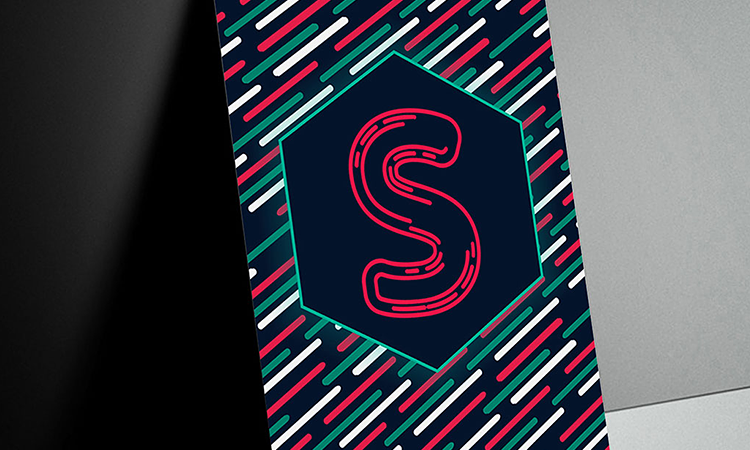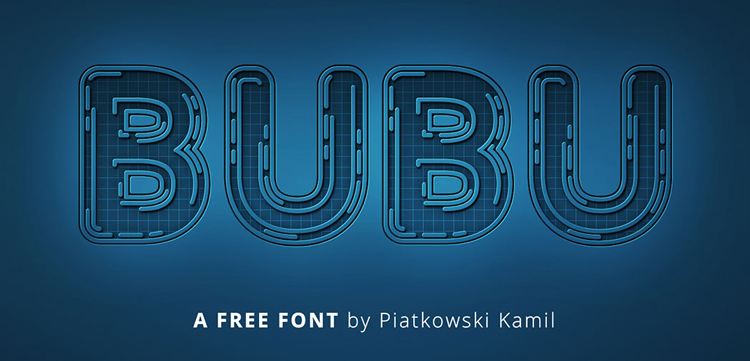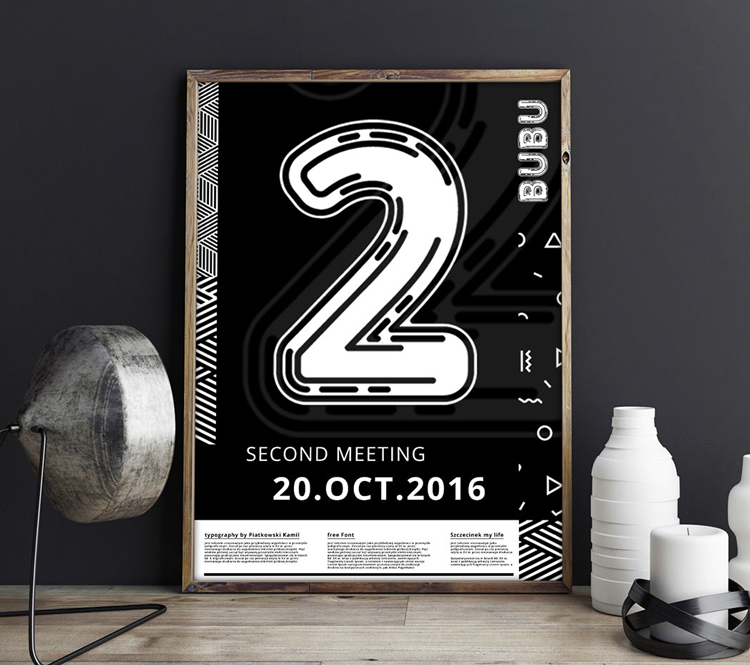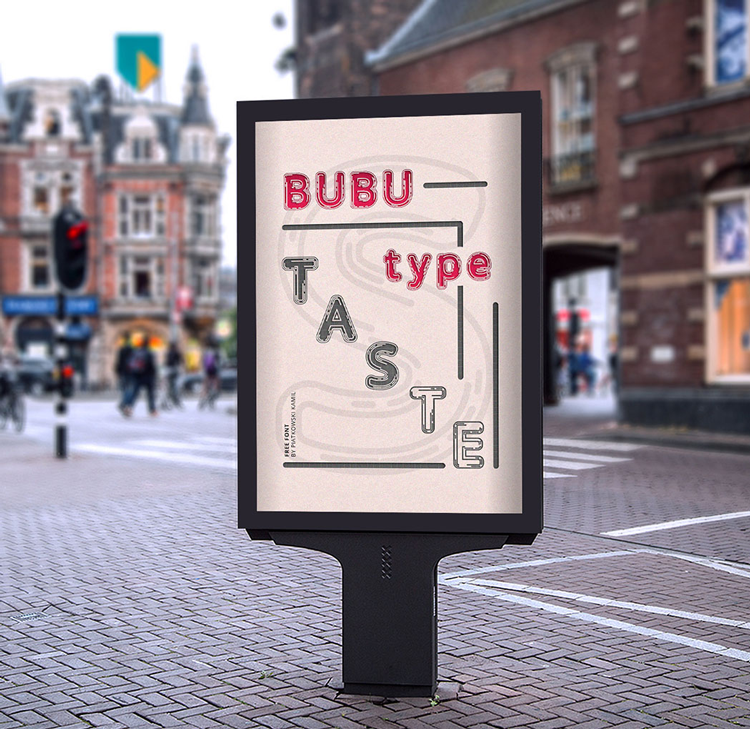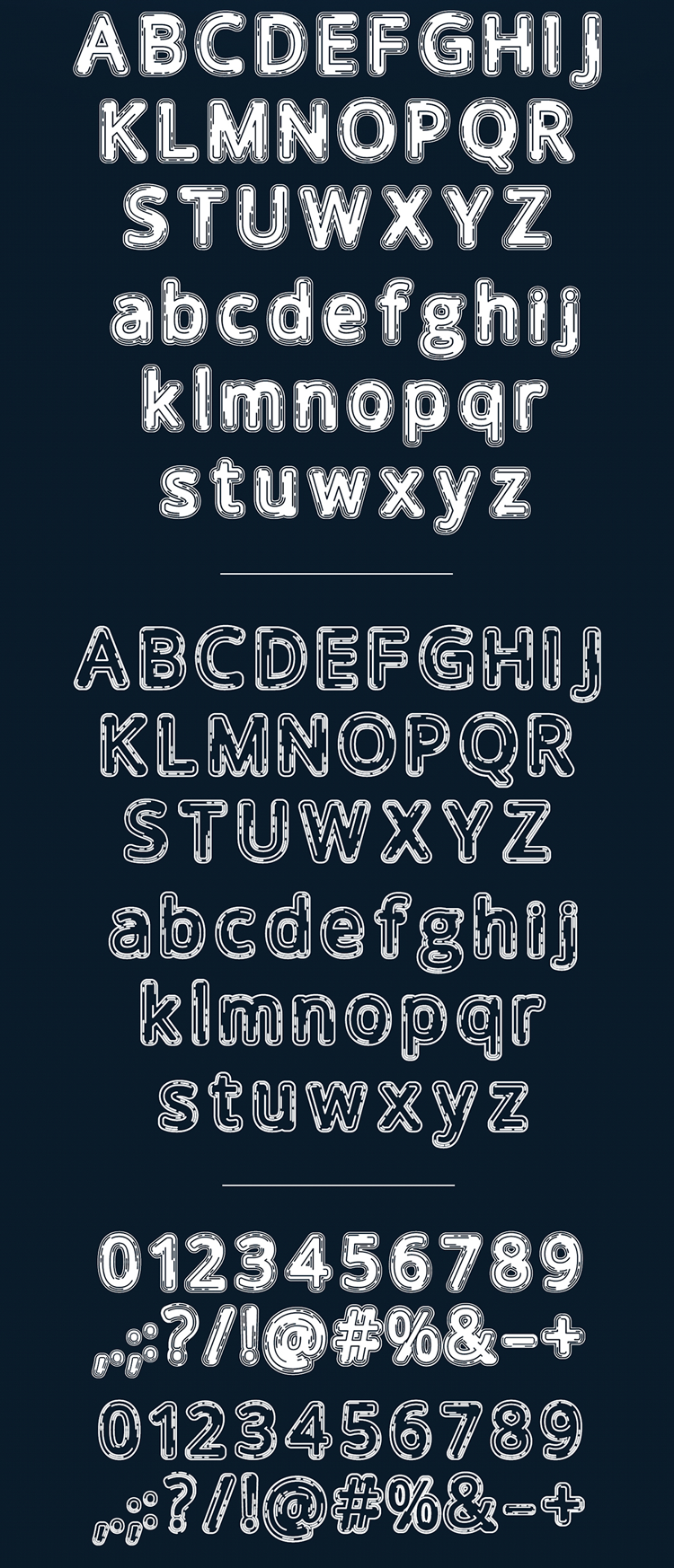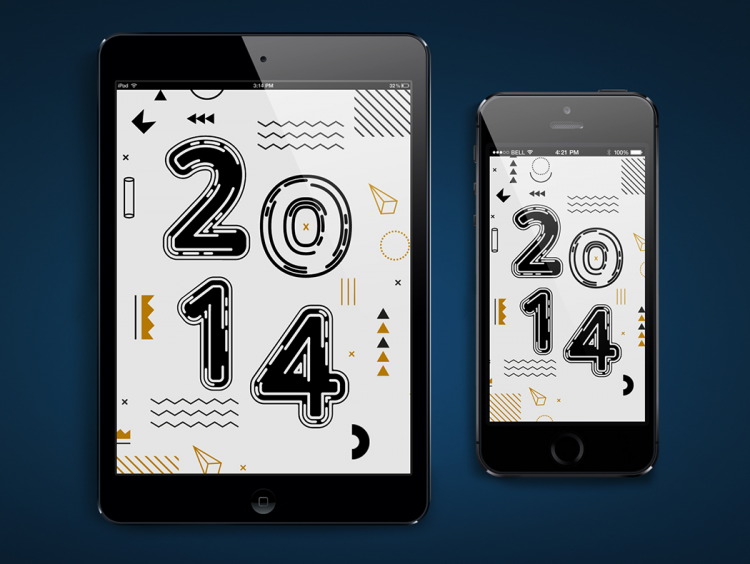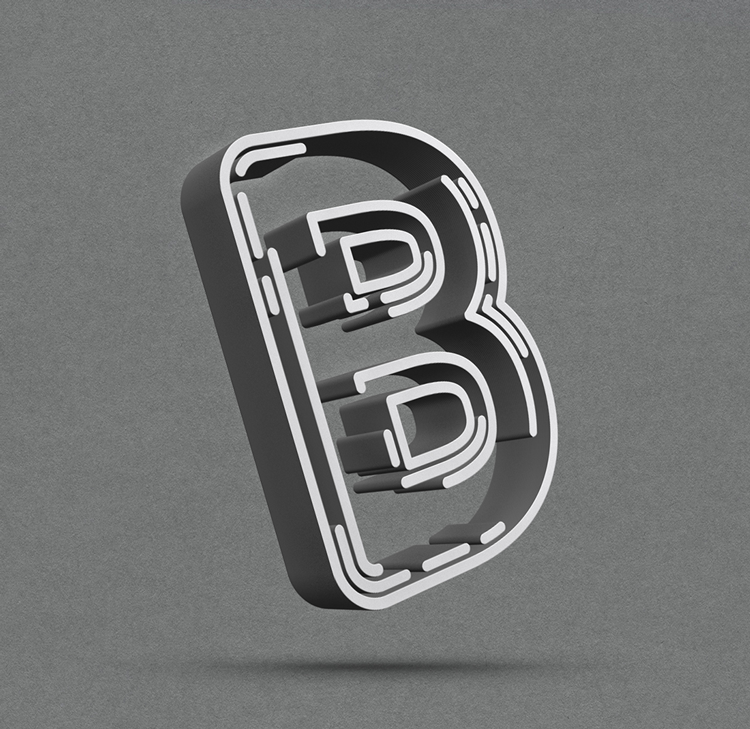
BUBU Font 2021.12.07 2016.11.23BUBU Fontは、フォントの外側のラインの内側に、影のようなラインのある立体的な印象の英語フォントです。オリジナリティのあるこのフォントは、1文字だけ大きなサイズで使っても、見る人の目を惹きつけます。ライセンス無料で使える商用可のフリーフォントです。ダウンロードBUBU Fontフォント情報ライセンス商用可カテゴリー英語 > オリジナルタグ楽しい、ユニーク、インパクト※当サイトはフォントの紹介サイトです。フォントを利用の際には必ず「フォントの利用について」をご覧ください。